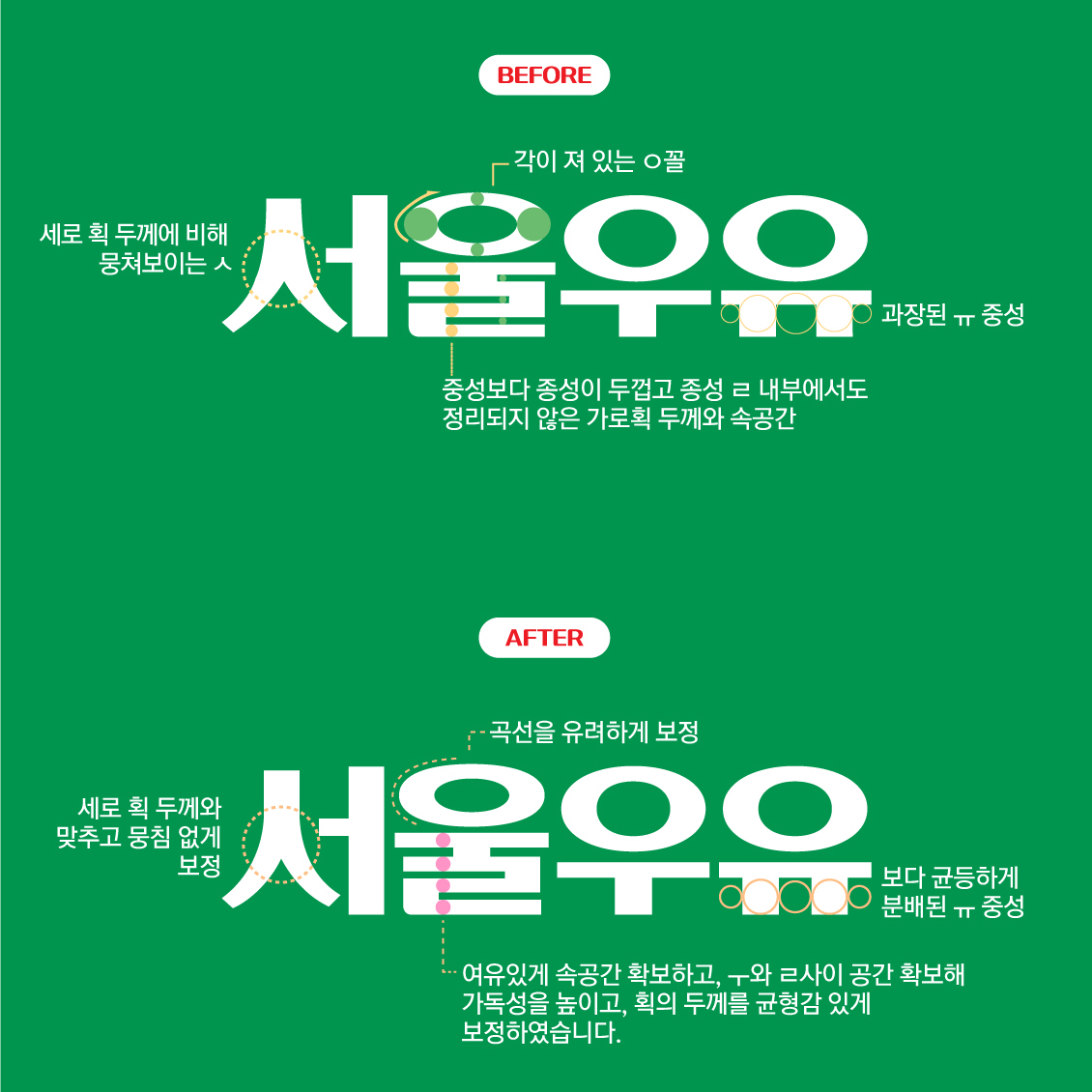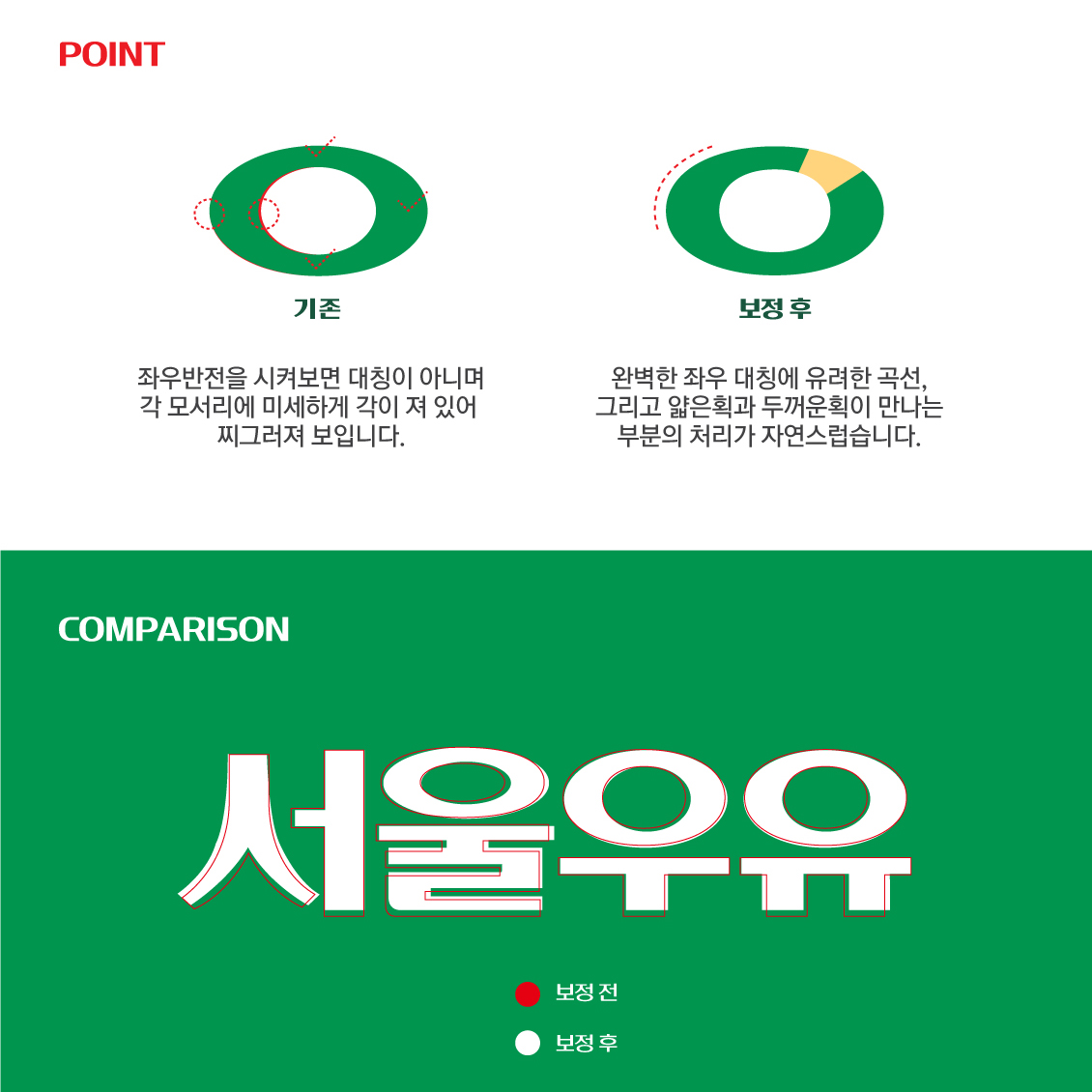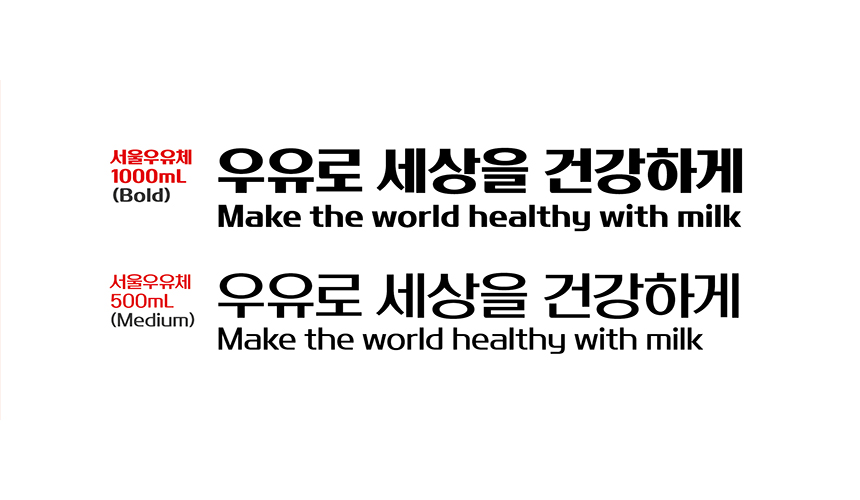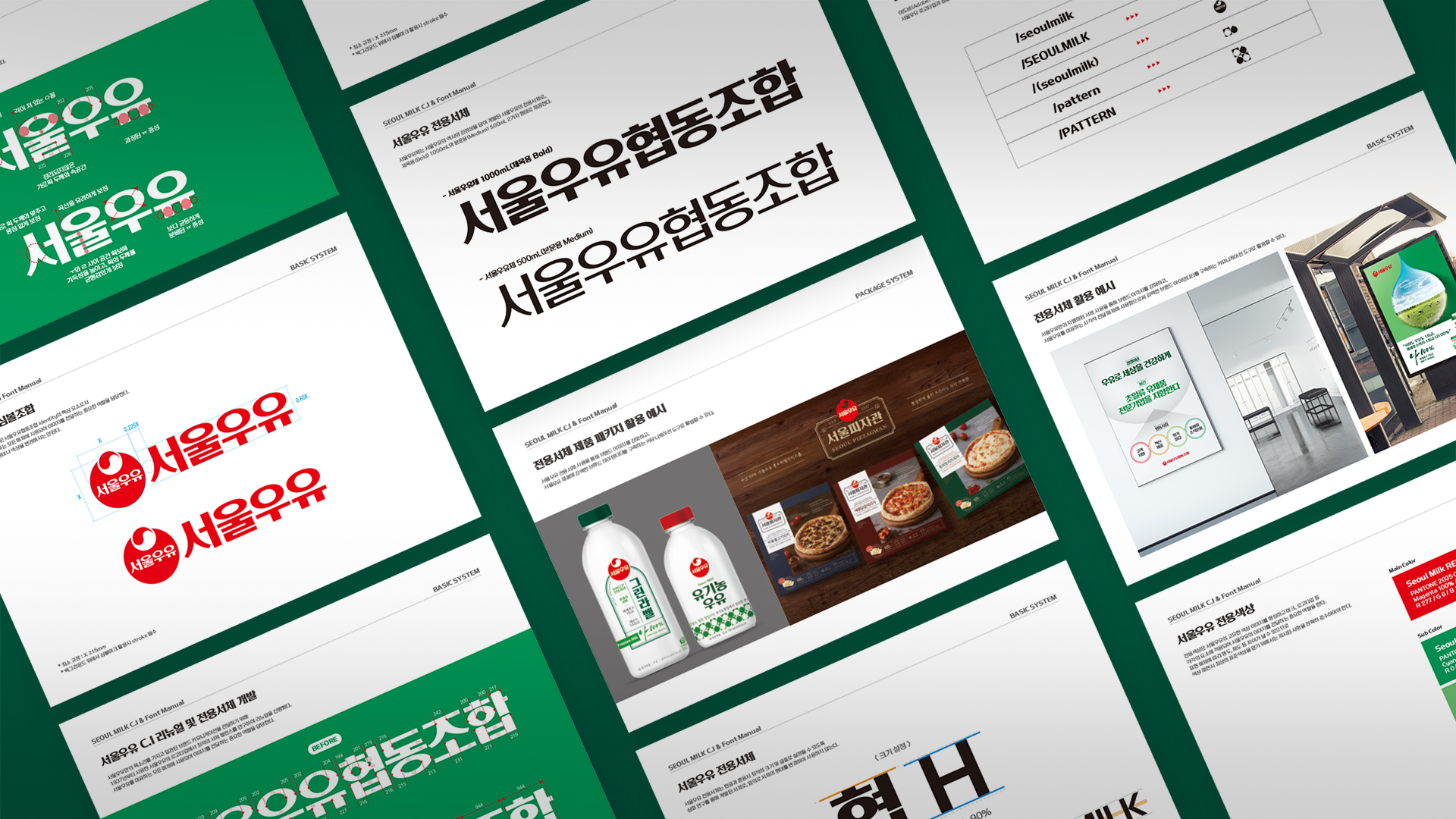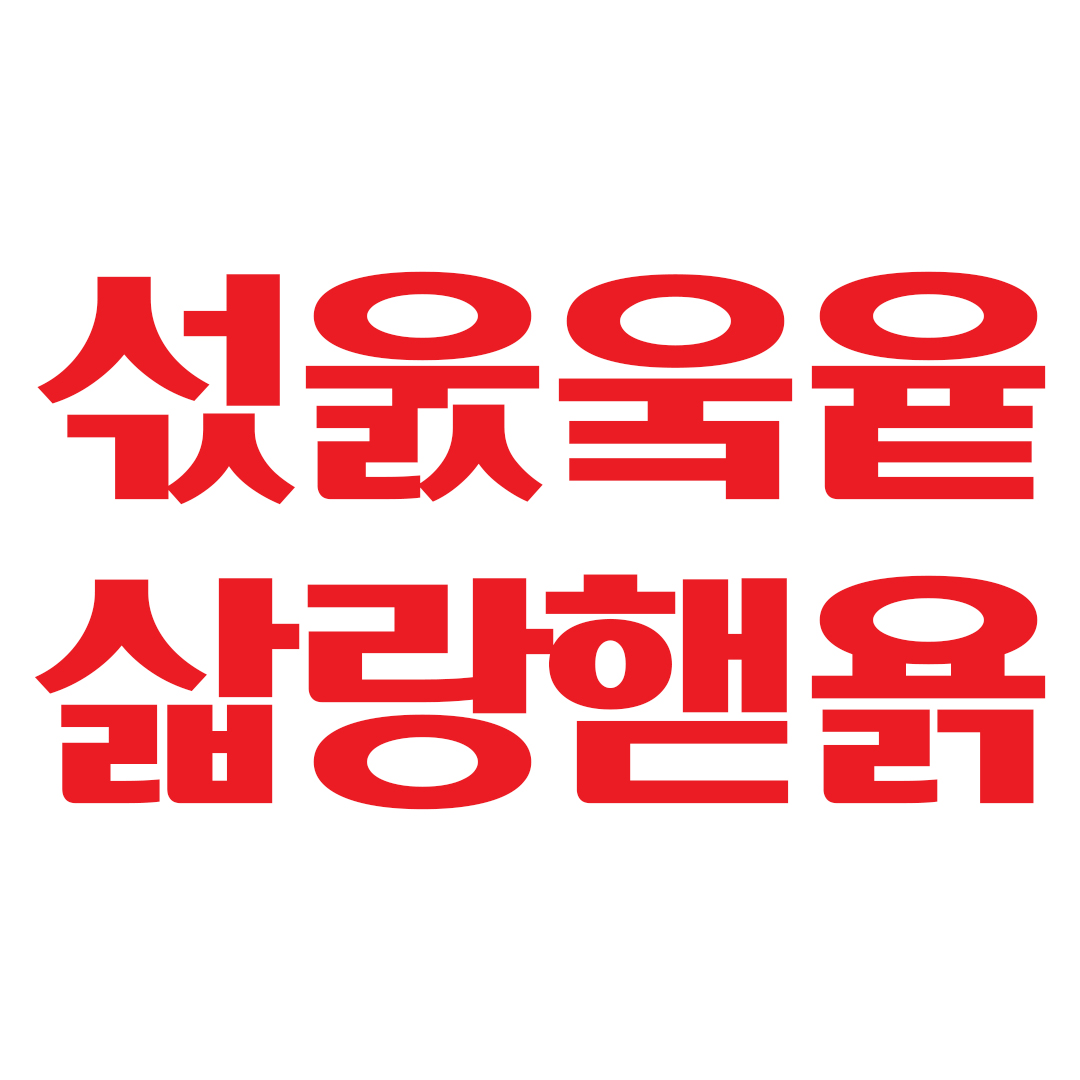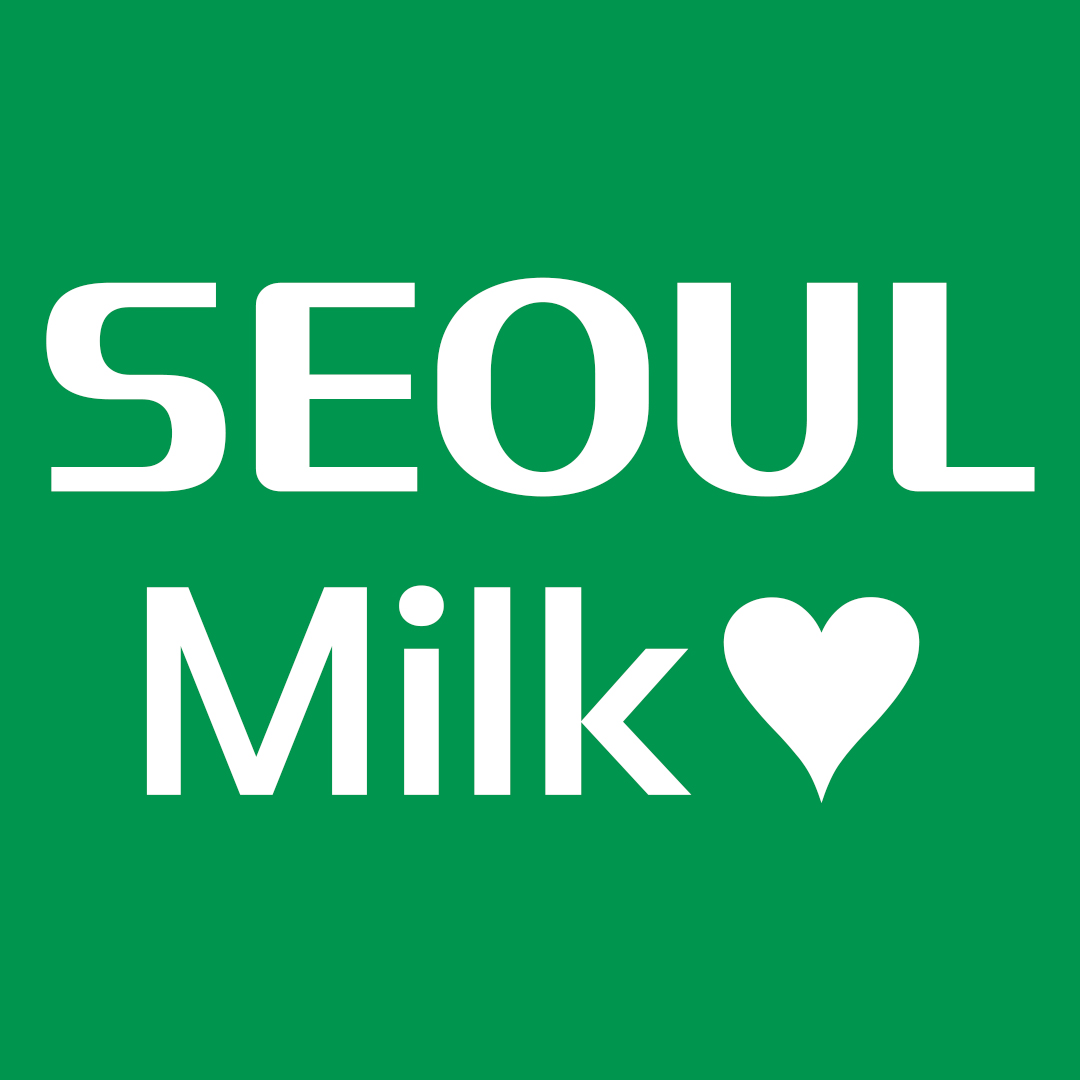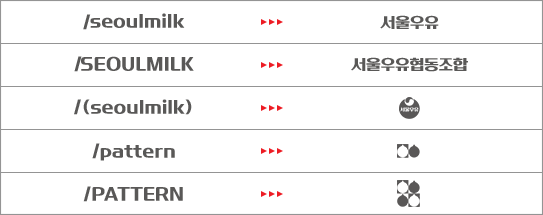
오늘 소개해드릴 전용서체는 1937년 창립 이래 지금까지 사용되어 온 서울우유의 한글 로고에서 착안하여 제작한 「서울우유체」입니다. 2021년 폰트릭스는 서울우유 디자인팀과 함께 기존 서울우유 CI를 모티브로 브랜드 아이덴티티를 담아 전용서체를 업그레이드하는 뜻깊은 작업을 했습니다. 업계 1위의 자리를 굳건히 지키고 있는 서울우유의 역사와 진정성을 담은, 서울우유체를 소개합니다.
보기 좋은 우유가 먹기도 좋다
서울우유의 로고마크는 고객과의 커뮤니케이션에 있어 서울우유만의 이미지를 대표하는 가장 중요한 요소 중 하나입니다. 그러한 상징성을 해치지 않으며 기존 디자인의 부족함을 개선하여 보다 안정감을 주는 것에 목표를 두었습니다. 각이 진 'ㅇ'꼴을 부드럽게 보정하고, 비율에 적절한 획의 두께 조정, 그리고 여유 있는 공간감을 통해 가독성을 높였습니다.
서울우유에서 아무래도 가장 많이 보이는 자음 'ㅇ'의 형태에 주목했습니다. 기존에 'ㅇ'꼴을 보면 대칭이 아닌 형태에 미세한 각이 져 찌그러져 보이는 아쉬움이 있었습니다. 이런 디테일한 부분을 보정하여 자연스럽고 부드럽게 라운드를 주었고, 서울우유가 보다 편안하게 다가갈 수 있는 이미지를 만들었습니다.
기발함 한 스푼, 활용도는 덤
서울우유체는 총 2가지 굵기로 파생되었습니다. 기존과 다르게 두께 표현 방식을 조금 달리 했는데요. 제목용으로 제작된 Bold체는 1000mL로, 본문용으로 제작된 Medium 굵기는 500mL입니다. 서울우유 디자인팀의 기지로 서울우유체만의 특별함이 생긴 것 같습니다. 두 가지 두께의 서울우유체는 현재 서울우유의 여러 제품명 그리고 텍스트가 필요한 다양한 곳에 활용되고 있습니다.
서울우유 섟욹웈윹 모두 가능!
한글 11,172자를 제작하여 모든 한글 자소를 표현할 수 있습니다. 또한 한글의 독창적인 디자인을 모티브로 영문 94자와 심볼 986자, 숫자도 잘 어우러지도록 디자인했습니다.
또한 어도비(Adobe) 등 합자(Ligature) 기능을 제공하는 프로그램 내에서 서울우유 로고타입과 심볼마크, 전용패턴 총 5가지 합자를 제공합니다. (왼쪽의 글씨를 쓰면 오른쪽의 이미지가 뿅!)
서울우유체 활용 백서🥛
서울우유체는 신뢰를 바탕으로 멋진 결과물을 만들어낸 브랜딩 사례가 되었다고 생각합니다. 기업의 올곧은 방향성과 컨셉, 디자인의 전문성이 만났을 때 완성도 높은 전용서체가 탄생합니다. 기업전용서체는 고객에게 무엇보다 강한 임팩트를 주고, 쉽게 각인되는 요소입니다. 많은 기업의 브랜드 마케팅 전략으로 자리 잡고 있는 타이포브랜딩을 함께합니다.